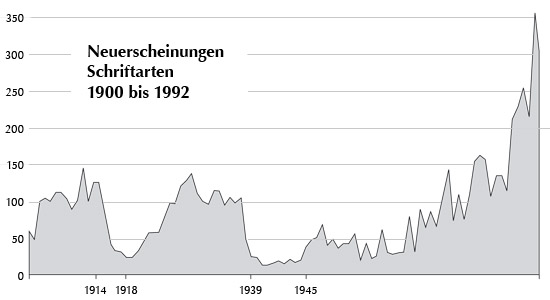
Ein wenig Statistik...
Auf der Basis von 7340 Schriften, deren Erscheinungsjahr in der Datenbank vorhanden ist, habe ich hier ein Diagramm mit den Neuerscheinungen pro Jahr aufgebaut. Man sieht sehr deutlich, wie der Schriftenausstoß als Folge beider Weltkriege deutlich sinkt. Nach dem Zweiten Weltkrieg hat die Schriftenbranche länger zur Erholung gebraucht als während der Weimarer Republik. Interessant?
Vielleicht sollte man auch die Korrelationen mit Einführungsjahren bedeutender technischer Neuerungen (Maschinensatz, Photosatz, Digitalisierung etc.) berücksichtigen. Mir scheint es so, als seien zur Einführung neuer Technicken zunächst die bekannten Schriften überführt worden und die Enwicklung neuer Schriften, die die jeweils neuen Techniken voll ausnutzten kam erst mit Verzögerung. Das hat sicher weniger Einfluss als die Kriege, aber es könnt »Zwischentäler« erklären.
Was ist hier mit Schriften gemeint?
Eine Familie à la Frutiger bedeutet eine Schrift? Oder werden die einzelnen Schriftschnitte als Schriften mitgezählt (die Kepler-Familie von R. Slimbach hat, als Extrembespiel, ca. 130 Schriftschnitte, das wären dann 130 Schriften…).
Wie verhält es sich bei einer Superfamily, wie der Stone oder Lucida?
Sind das vorrangig in Deutschland erschienene Schriften?
Wieviel Schriften gab es zu welcher Zeit, wieviel von diesen sind erfasst?
Welche Länder werden mitgezählt?
Wie sieht es mit nicht-lateinischen Druckschriften aus?
Das mit der Statistik ist immer so ne Sache.
Genau. Wir hatten das hier schon einmal besprochen, im Thread „Weißt Du, wieviel Sternlein stehn...“ Nur eine Zählung nach Schriftschnitten macht wirklich Sinn. Die Anzahl der Schriftfamilien ist ein anderer Wert, der auch ermittelt werden kann. Demnach wird die Kepler mit derzeit 168 Schnitten (Linotype) als 168 Schriften gezählt. Bei der Zählung der Familien kommt hier 1 heraus – oder auch mehr, das ist reine Festlegungssache. Man muss nur sagen, wie diese Zahl zustande kommt.
Meine Zählmethode wird dann auf das veröffentlichte Artwork bezogen sein, so wie auch ein Expertfont als Schrift zählt. So muss man das dann auch einordnen.
Die Schriften stammen aus Europa, Amerika, Asien und Australien.
Du wirst lachen – die reine Namensliste sollte bis 1992, da habe ich abgeschnitten – so gut wie alle bis dahin herausgebrachten Schriften des 20. Jahrhunderts beinhalten. Das hier gezeigte Diagramm basiert auf den genannten 7340. Das entspricht mindestens 3,5 %, sehr wahrscheinlich erheblich mehr. Das dürfte „statistisch signifikant“ sein.
Alle, die Schriftgießereien oder Foundries hervorbringen.
Nach Namen erfasst, derzeit keine Bildbeispiele oder PDFs.
Natürlich, keine Frage. Aber die bisher gemachten Aussagen sollten durchaus Gültigkeit besitzen. Man muss das ja nicht überinterpretieren.